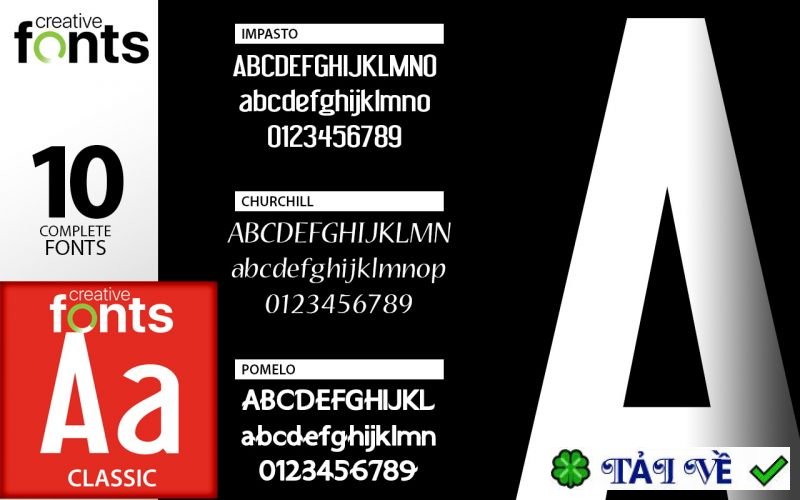
Summitsoft Traditional Fonts Collection 2022 Font chữ cổ điển tinh tế
Muốn thổi hồn cổ điển, tinh tế vào các thiết kế của bạn? ✨ Summitsoft Traditional Fonts Collection 2022 chính là lựa chọn tuyệt vời! 📜 Bộ sưu tập này mang đến tuyển tập phong phú các font chữ serif và script đẹp mắt, được tuyển chọn kỹ lưỡng để tạo nên vẻ sang trọng, hoài cổ vượt thời gian. 🌟 Dù bạn cần cho logo, thiệp mời, hay bất kỳ dự án nào, những font chữ chất lượng cao này sẽ giúp tác phẩm của bạn trở nên độc đáo và thu hút hơn bao giờ hết. 💖
Tổng quan về Summitsoft Traditional Fonts Collection: Bộ sưu tập phông chữ mang phong cách truyền thống
Summitsoft là một công ty phát triển phần mềm, cung cấp nhiều công cụ thiết kế và năng suất. Một trong những sản phẩm của họ là Summitsoft Traditional Fonts Collection, một tuyển tập các phông chữ mang tính thẩm mỹ cổ điển và vượt thời gian. Những phông chữ này được thiết kế để gợi lên cảm giác sang trọng, đậm nét truyền thống, đồng thời phù hợp với nhiều dự án thiết kế khác nhau, bao gồm thiết kế đồ họa, xây dựng thương hiệu, thiệp mời, bảng hiệu, v.v.
Bộ sưu tập Summitsoft Traditional Fonts Collection bao gồm nhiều kiểu chữ lấy cảm hứng từ thư pháp cổ điển, phong cách vintage và các mẫu chữ truyền thống. Những phông chữ này thường có đường cong mềm mại, chi tiết trang trí tỉ mỉ và phong cách tinh tế, gợi nhớ đến các giai đoạn lịch sử và phong trào nghệ thuật khác nhau.
Các bộ sưu tập con bao gồm:
- Phông chữ cổ điển
- Phông chữ thư pháp
- Phông chữ sáng tạo
- Phông chữ thiết kế
- Phông chữ độc đáo
- Phông chữ viết tay